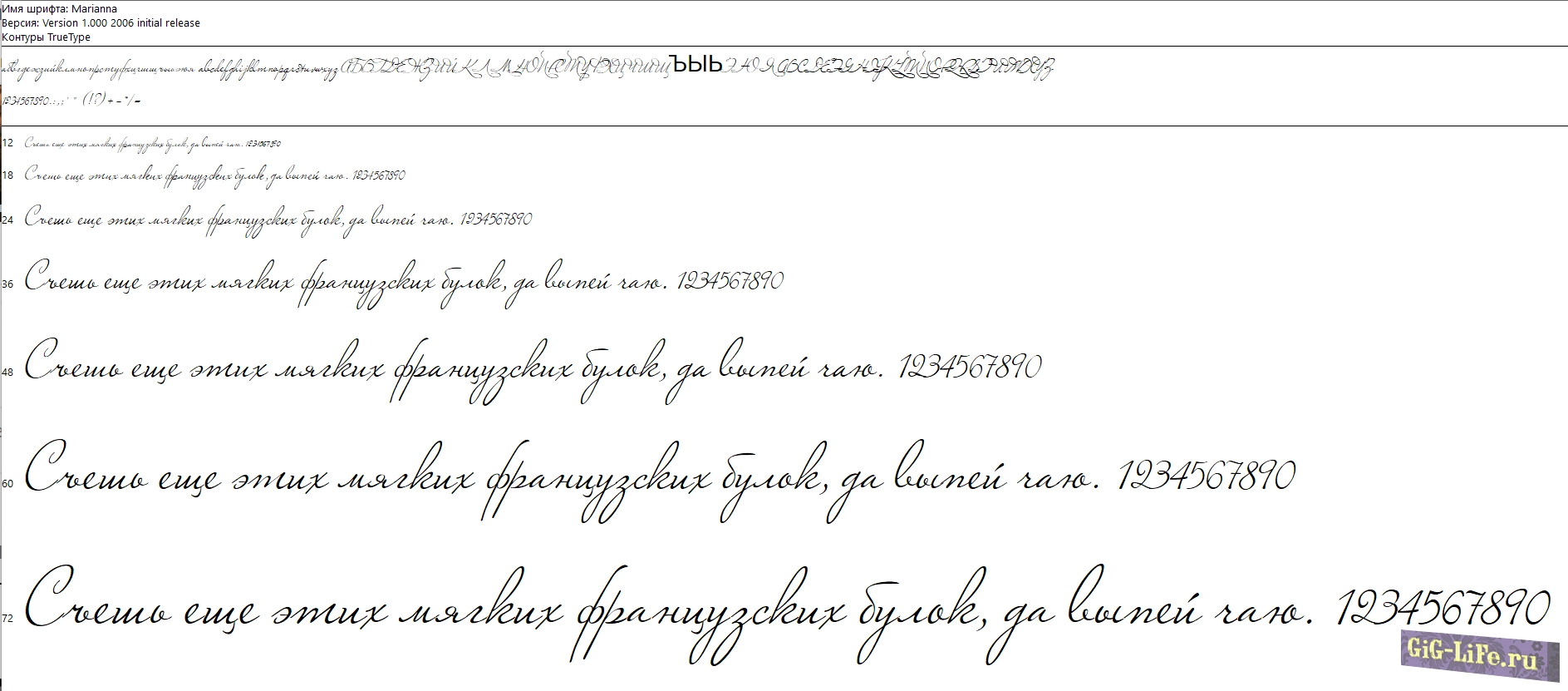
Шрифт — Марианна | Marianne
Вашему вниманию представляется фантастический рукописный шрифт Русского языка, который имеет потрясающее качество и может быть применен в различных видах творческих работ.
Этот уникальный шрифт предоставляет возможность добавить особый шарм и оригинальность в ваши проекты. Теперь у вас есть возможность украсить свои творческие идеи с использованием этого потрясающего типографического решения.
Будьте уверены, что ваша работа будет привлекать внимание и оставаться запоминающейся благодаря этому фантастическому рукописному шрифту.